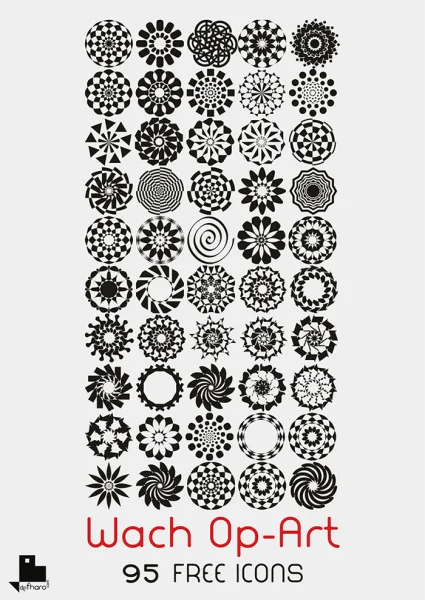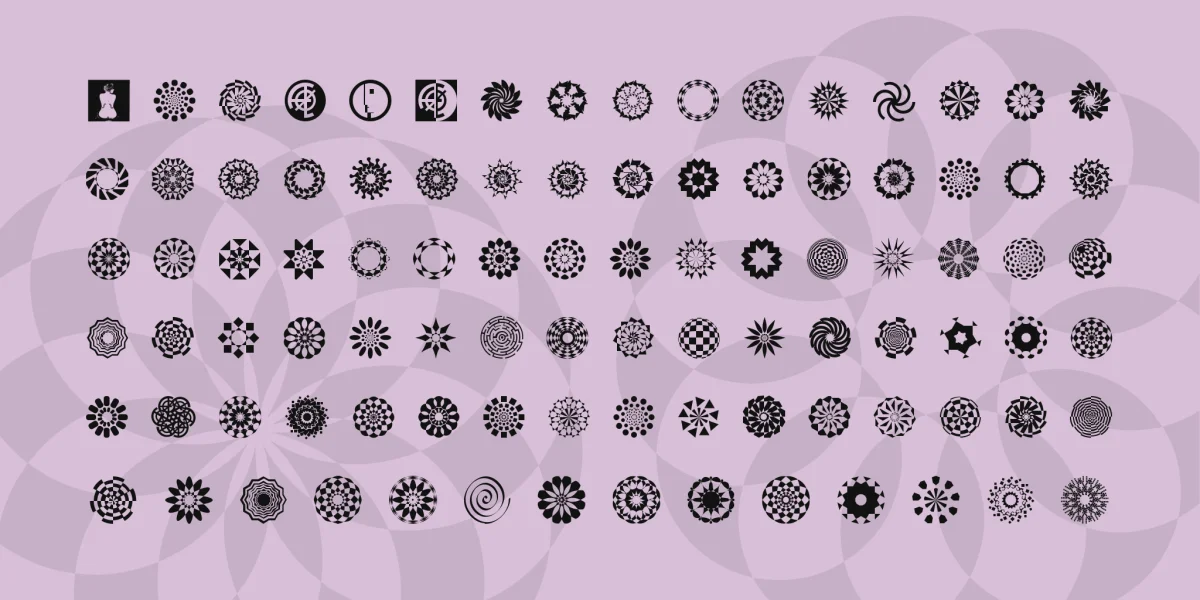
Esta colección de iconos esta inspirada por los diseños de la colección de relojes de pulsera ÆØ Watches "The only one collection", más concretamente a la serie Op art creada por mí al final de los 80. defharo.com/diseño-grafico/aeo-watch-relojes-de-diseno/Puedes usarlo para diseño de posters o logos.Thank you for your interest in my symbol font :) This font is free for personal use only.If you are interested in commercial use, you can buy the license in defharo.com/diseño-grafico/95-clips-online-gratis/You may redistribute my fonts on your site as long as credit is defharo.com as the original author.Donations are always welcome :)